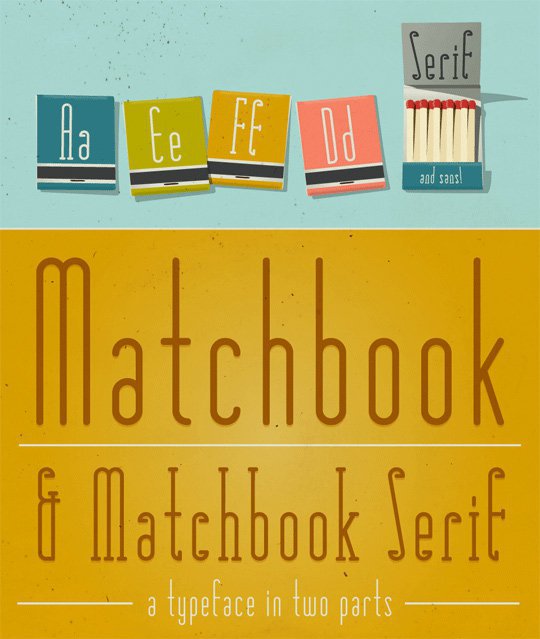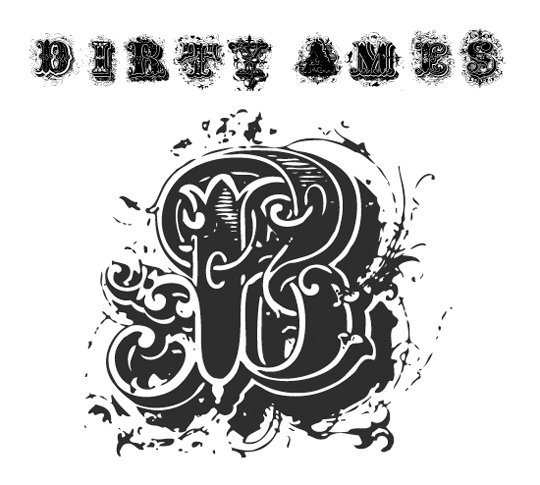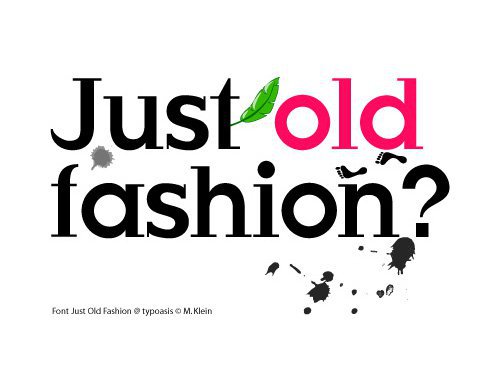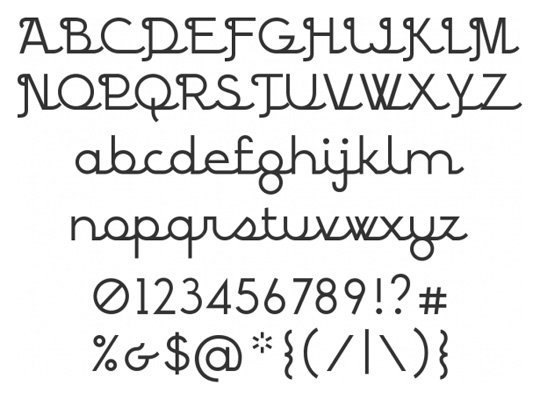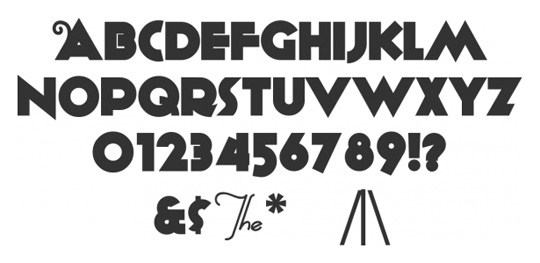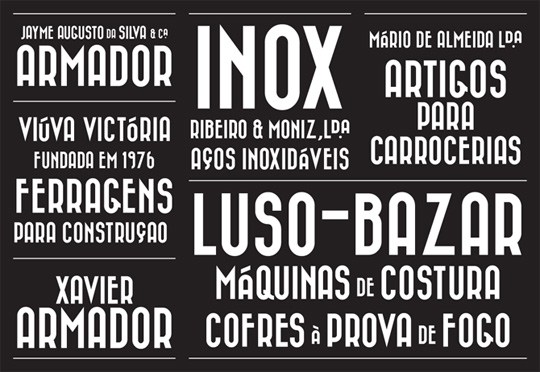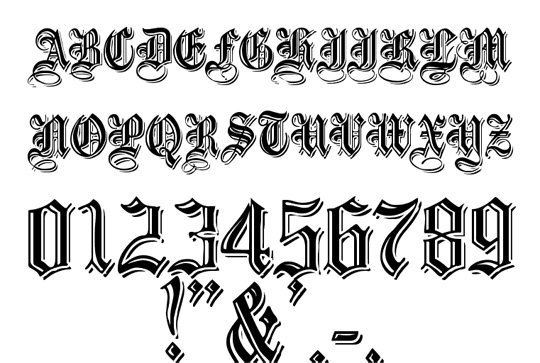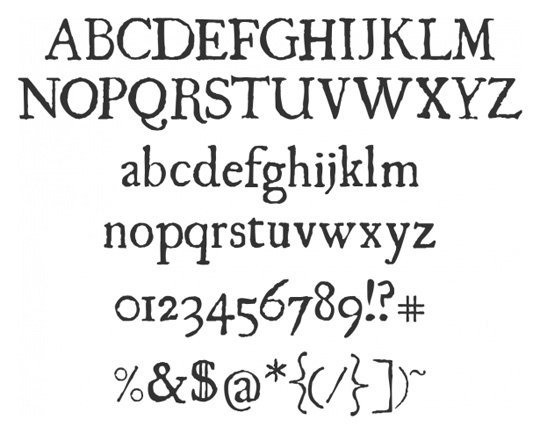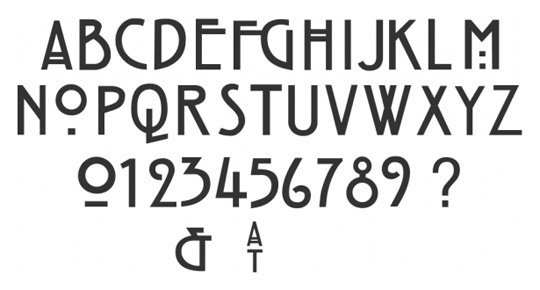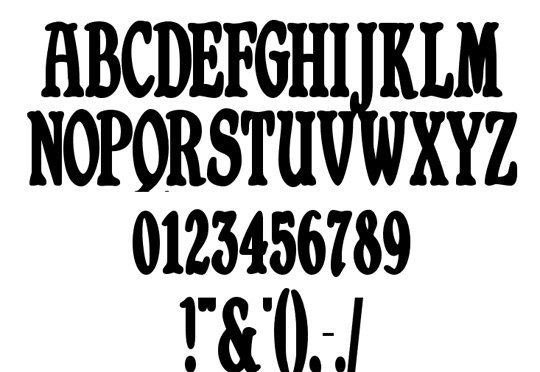
Бесплатные винтажные и ретро шрифты
Дизайн в стиле ретро предназначен для отсылки в прошлое, и желательно, не меньше чем лет на 40-50. Такой дизайн передает особую атмосферу, придает проекту выдержанность хорошего коньяка и даже немного играет на нащей ностальгии. Для этого используют различные методы — например, элементы в винтажном стиле, ретро паттерны, текстуры, цветовые гаммы. Важное место здесь занимает типографика. Для свежей подборки мы нашли 17 самых атмосферных (и бесплатных!) ретро шрифтов, которые отражают настроение 1920—1960 годов прошлого века.
Matchbook
Bazar, Medium
Embossed Black
Ugly Qua
Hill House
Shrewsbury-Condensed Bold
Caslon
Seaside Resort
Fontleroy Brown
Fusty Saddle
Dirty Ames
Just Old Fashion
Goudy Bookletter 1911
Circus Ornate
BP Script
Rocket Script
Anagram